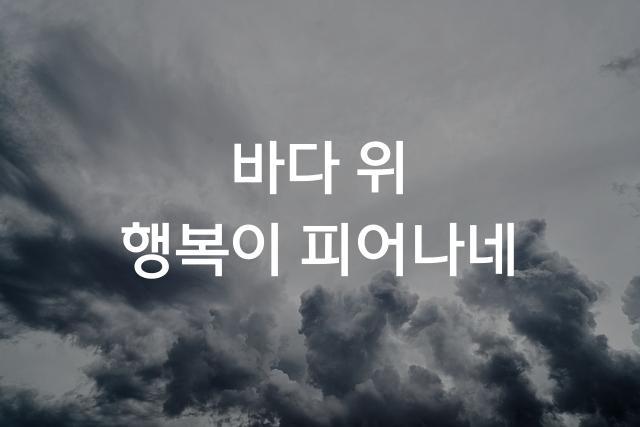
원스토어 모바일POP체는 둥근 고딕 형태로 제작되어 부드러움과 친근함을 강조합니다. 귀여운 감성을 담아 유저들에게 친숙하게 다가가는 폰트입니다.
원스토어 모바일POP체은(는)
기본 고딕, 둥근 스타일, 귀여운 스타일, 감성적인, 부드러움, 복실복실 계열의 생김새를 가지고 있으며
디지털 광고, 카페 메뉴, 소셜 미디어 등에서 자주 활용되며, 효과적인 메시지 전달에 적합합니다.
이 폰트는 음식/식음료, 라이프스타일, 소매/유통 분야에 잘 어울리며,
귀여운, 창의적인, 재미있는 느낌을 담고 있는 것이 특징입니다.